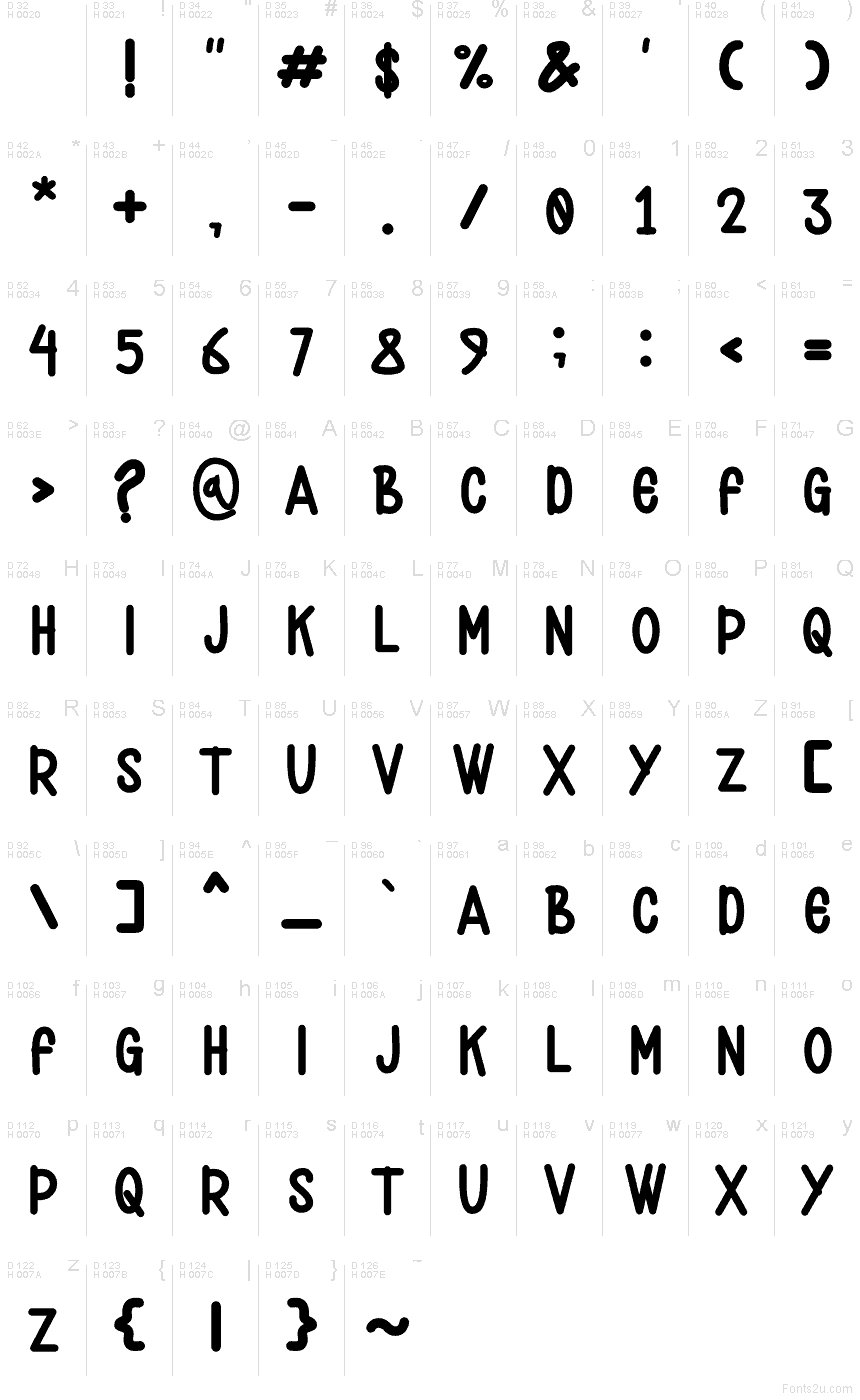
Melianes de Futuristype es una fuente gratuita de estilo cómic redondeado con un toque alegre y dibujado a mano. Las letras se sienten suaves y robustas, con trazos verticales fluidos y curvas amplias que mantienen un aire desenfadado sin llegar a ser demasiado pulido, logrando un estilo cartoon amigable sin caer en lo infantil.
Es ideal para titulares de carteles, envases, pegatinas, portadas de libros infantiles y diseños para redes sociales donde un poco de calidez ayuda a que el mensaje llegue rápido. Al ser una fuente gratuita, Melianes también funciona muy bien en eslóganes y elementos editoriales divertidos, ya que su ritmo orgánico y formas sencillas destacan mejor cuando el texto es breve.